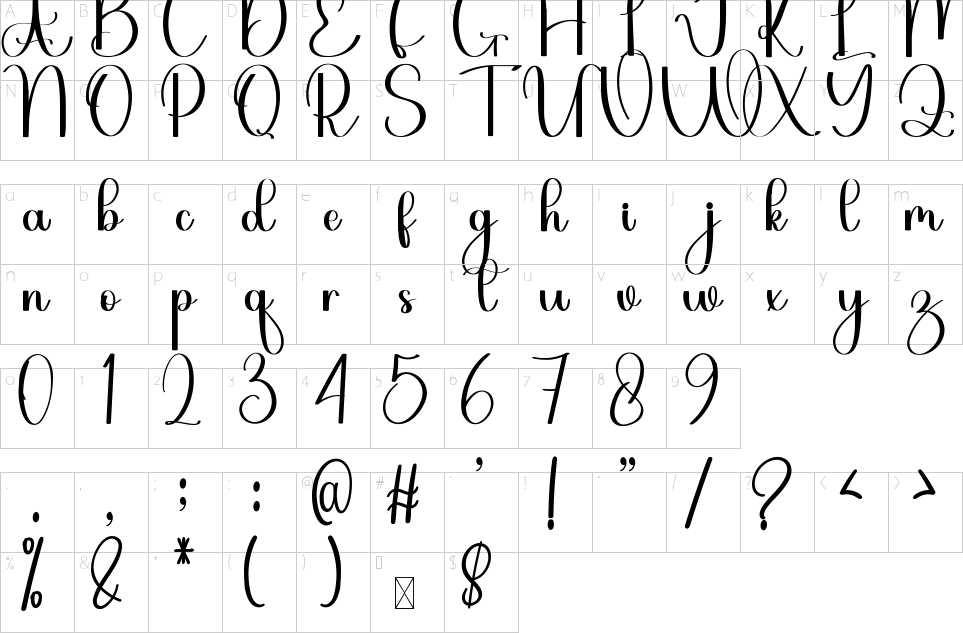
Anabel Christmas é uma fonte de estilo natalino feita para dar um toque especial às suas criações natalinas. Ela foi criada pelo designer desconhecido InermediaSTUDIO, e já foi baixada 601 vezes. Esta fonte é perfeita para decorar seus designs natalinos com um charme único e personalizado. Seja para presentear sua família com um coração de Natal personalizado ou para imprimir cartões de Natal surpreendentes, Anabel Christmas pode ser a escolha ideal. Com seu design natalino e seu download fácil para Windows e Mac, ela certamente fará sua campanha de Natal ser destaca no meio da multidão.